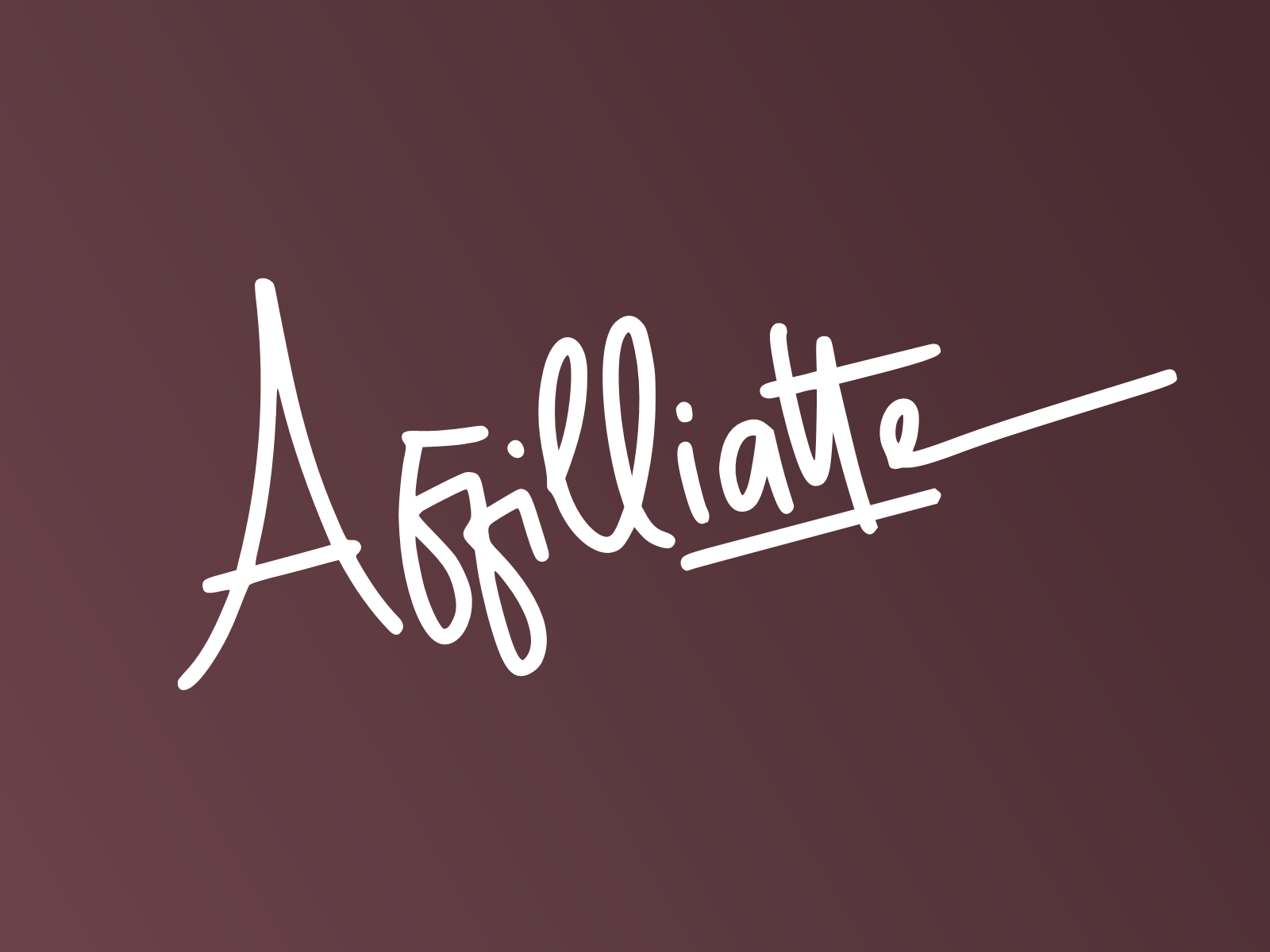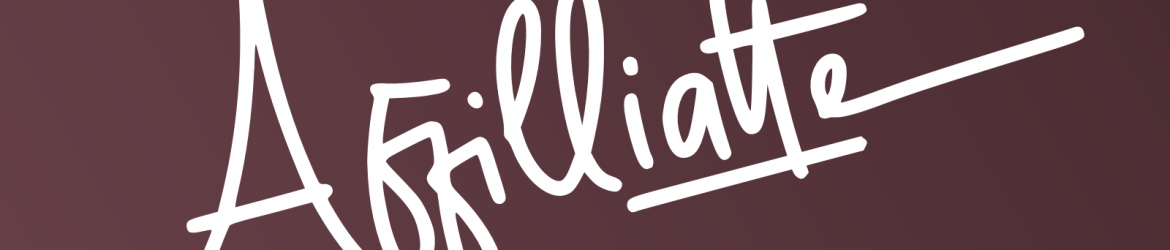
Esta fonte é uma elegante dupla, composta por letras manuscritas e tipografia sans serif. Ela se destaca pela suavidade de suas curvas, tornando-a perfeita para estilos de marcação ou design editorial com um toque delicado e sofisticado. O fato de ser PUA encoded permite que você tenha acesso a todos os símbolos e adesivos sem qualquer dificuldade. Seja para uma campanha de moda ou conteúdo impecável, esta fonte atinge o equilíbrio perfeito entre elegância e delicadeza. É um verdadeiro tesouro para designers apaixonados em buscar novas maneiras criativas de expressar suas ideias no mundo da design gráfico.